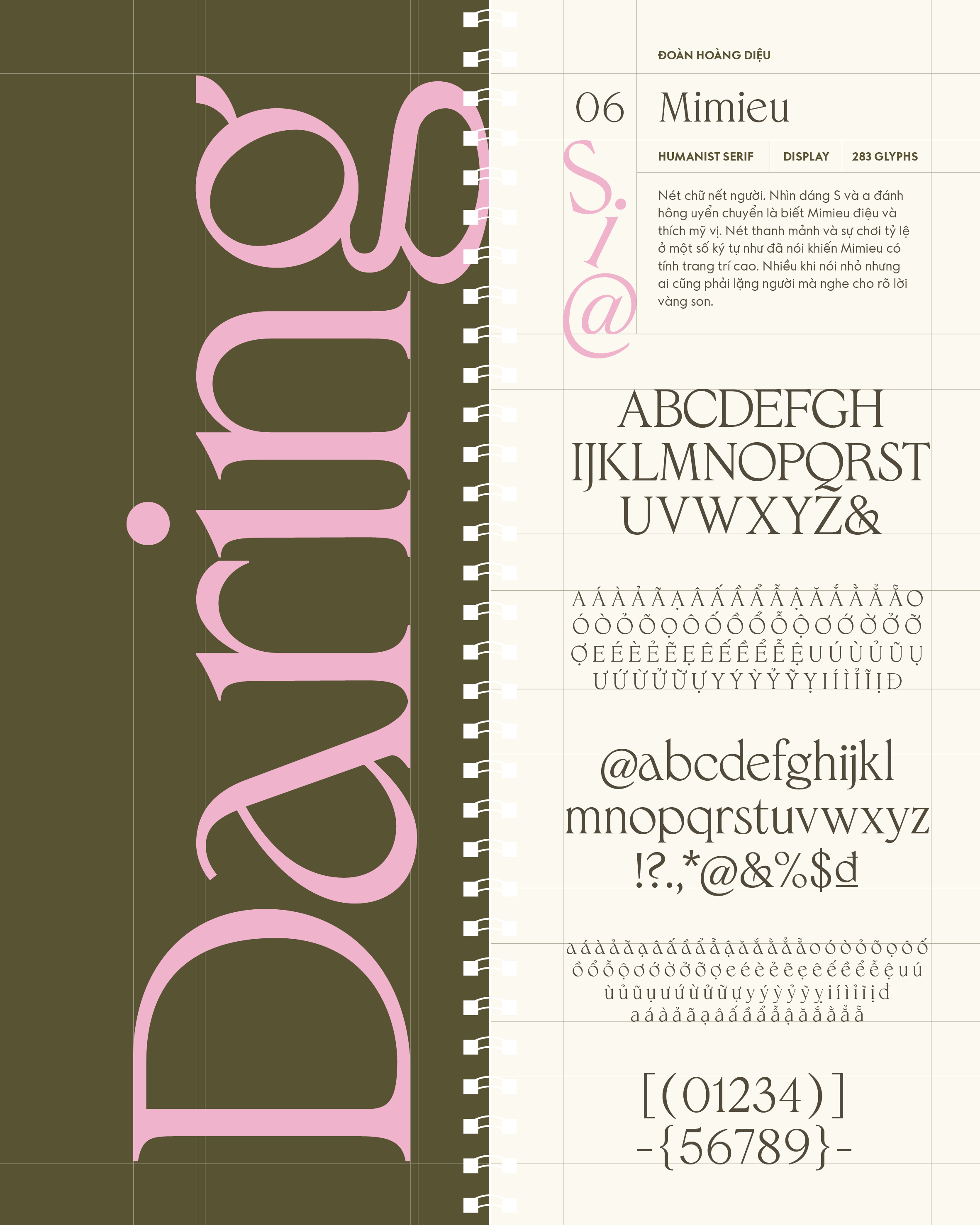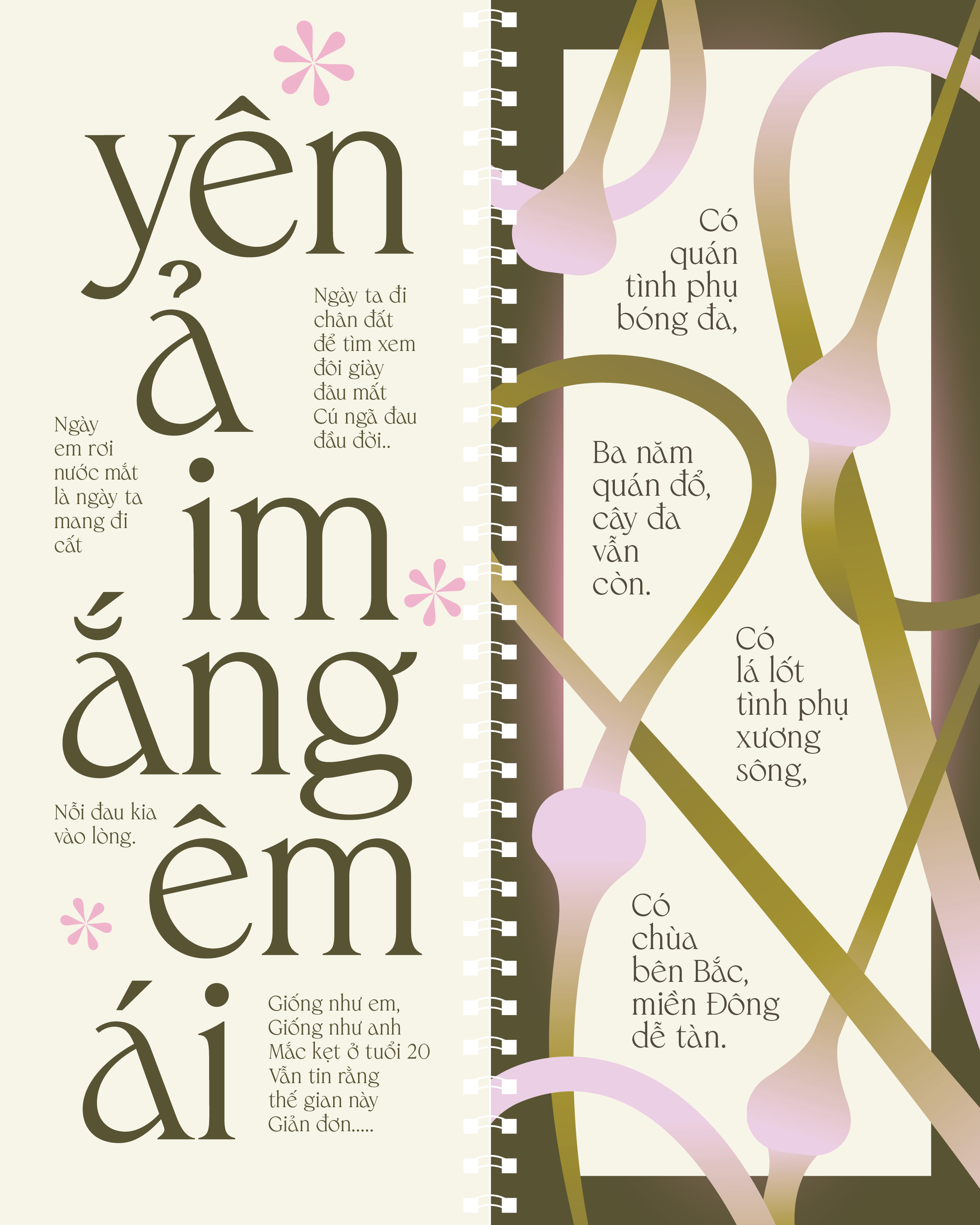
Mimieu
Về Mimieu: Nét chữ nết người. Nhìn dáng S và a đánh hông uyển chuyển là biết Mimieu điệu và thích mỹ vị. Nét thanh mảnh và sự chơi tỷ lệ ở một số ký tự như đã nói khiến Mimieu có tính trang trí cao. Nhiều khi nói nhỏ nhưng ai cũng phải lặng người mà nghe cho rõ lời vàng son.
Humanist Serif
Display
Đoàn Hoàng Diệu
Mimieu
Daring
Mimieu
One Memory
Mimieu
Tuổi 20
Mimieu
Chợt mộng tan